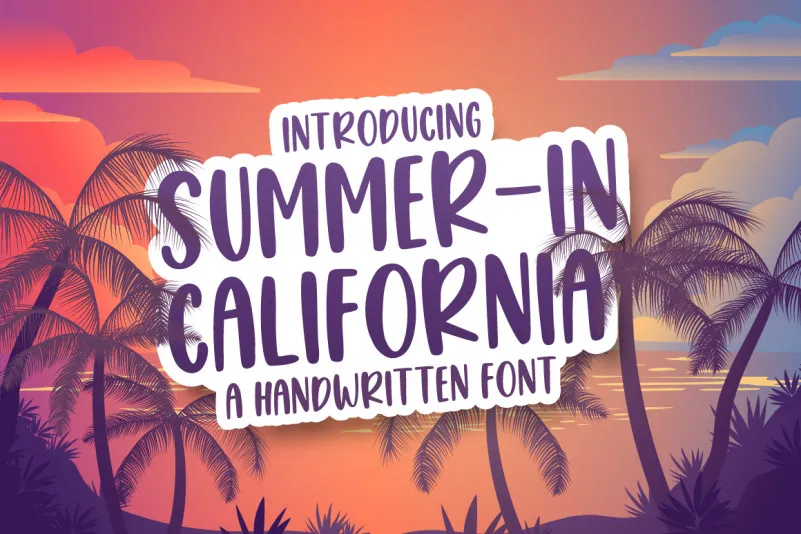
Summer in California Font – Download Grátis
Descubra a autêntica encantadora do verão na Califórnia com Summer in California Font. Esta elegante e atrevida font, cuidadosamente criada pelo designer jimtypestudio, é perfeita para qualquer projeto que você possa imaginar. Com sua tipografia de display, ela se destaca em elementos digitais como logos e branding, arte para camisetas, designs infantis, criações artesanais e até mesmo em cartões de visita ou estilos de citação. Suas letras maiúsculas fortes e altas são ideais para criar um visual único que captura a essência do verão vibrante na Califórnia. Este é o tipo certo para dar vida à sua marca, tornando-a ainda mais memorável e atraente. Não deixe de experimentar Summer in California Font em seu próximo projeto criativo!